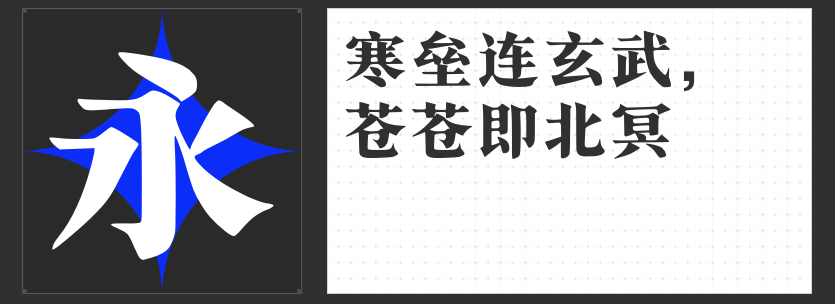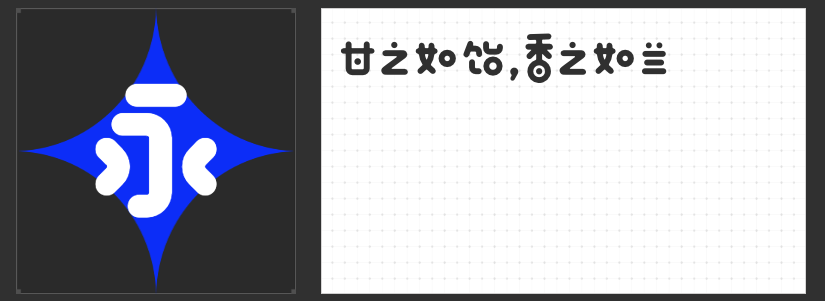
四款现代感创意字体推荐:打破常规,重塑视觉张力
在设计中,字体的选择是传递风格与情感的关键。以下四款非免费但极具现代感的创意字体,通过独特的形态与结构,为作品注入科技、活力与艺术气息,无论是品牌视觉、海报设计还是数字媒体,都能成为点睛之笔。
一、励字志向黑简 大粗
这款字体以黑体为骨架,融合圆体基因,在笔画拐角处采用圆角设计,打破传统黑体的冷硬感。其字面饱满、结构稳定,粗壮的笔画赋予文字力量感,而圆角的加入则让整体更显灵动,避免视觉疲劳。尤其在屏幕显示中,圆角设计能优化小字号下的可读性,适合科技产品海报、企业标语等场景,传递专业与亲和并存的现代气质。
二、励字圆梦简 中黑
以直线笔画为主,辅以竖折替代弧线,这款字体在简洁中暗藏巧思。起笔、收笔与转折处的自然圆弧,让硬朗的直线结构多了几分柔和,中宫松散的设计则赋予文字呼吸感。作为一款拥有三种字重的家族字体,它既能以粗体撑起标题的视觉冲击力,也能用细体保证正文的阅读流畅性,无论是商务报告、文艺杂志还是UI界面,都能实现风格与功能的平衡。
三、机甲宋玄武号
将宋体的书卷气与机甲的硬核科技感碰撞,这款字体堪称“赛博国风”的典范。它保留了宋体的横细竖粗、捺脚特征,却在笔画中融入机甲的锐利棱角与金属质感,如竖钩的折角如刀锋般凌厉,捺画末端则似机械关节般精密。这种冲突与融合的视觉张力,使其成为科幻电影海报、游戏LOGO或未来感产品的绝佳选择,瞬间提升作品的辨识度与沉浸感。
四、创客贴软糖体
如其名,这款字体仿佛由软糯的糖果捏制而成——笔画圆润无棱角,字形大小错落有致,打破传统字体的规整感。它用“不完美”的形态传递出天真与童趣,却因统一的圆弧风格而不显杂乱。无论是儿童品牌、手账贴纸还是社交媒体表情包,创客贴软糖体都能以俏皮姿态拉近与受众的距离,让设计在严肃与诙谐间自由切换。
这四款字体以现代审美为锚点,通过创新结构与风格碰撞,为设计开辟了更多可能性。